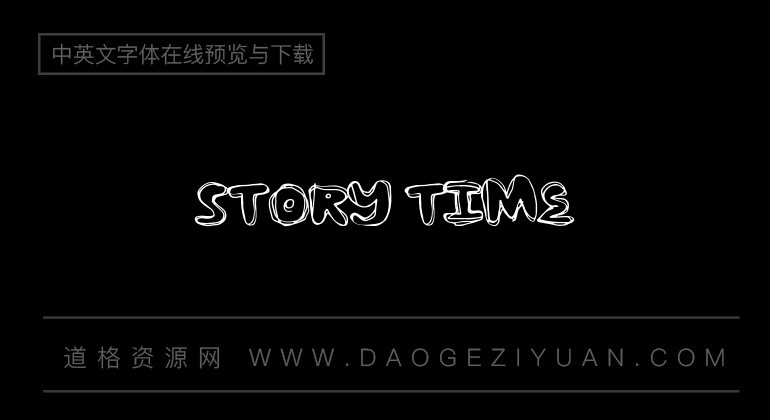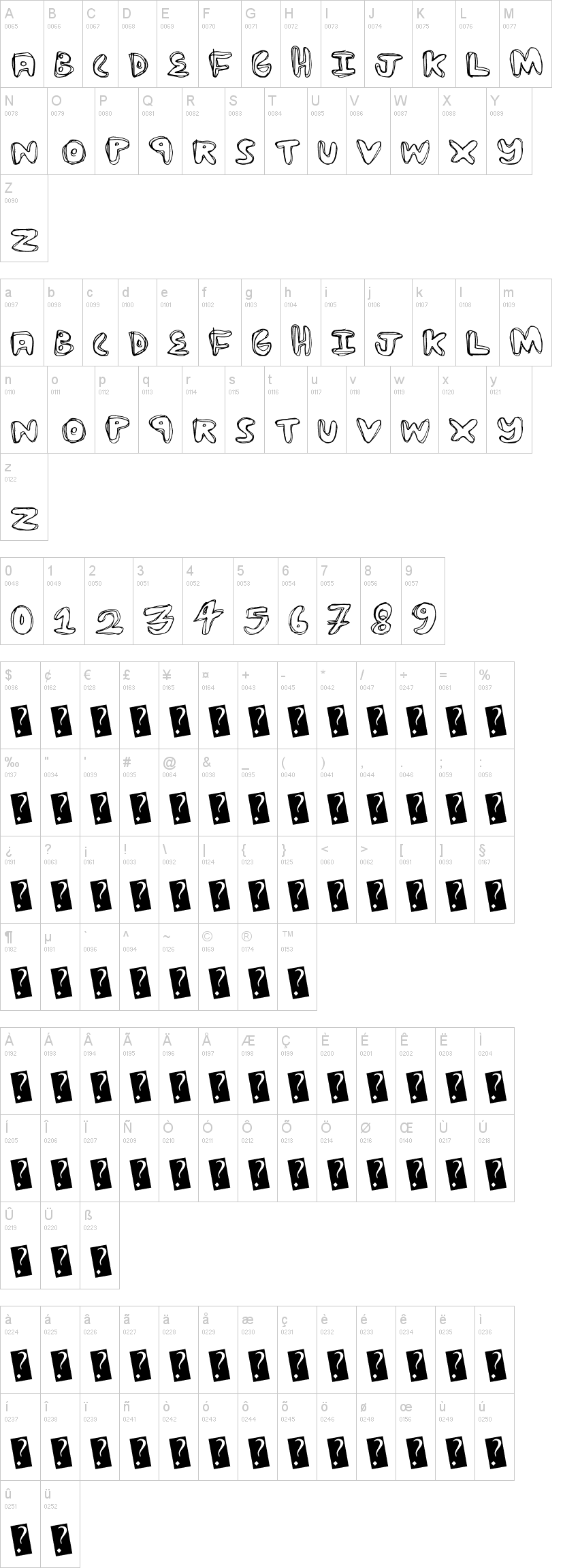
Story Time 是一款现代欧美风格字体,由 Fontfabric 公司设计,具有轻松、活泼、温暖的设计风格。它有着良好的可读性,可以用于各种类型的文本,如书籍、文章、广告等。Story Time 字体具有清晰的线条,更加精致的字形,以及更加丰富的字体组合,可以满足不同的设计需求。内容介绍
Story Time是一款非常不错的手写艺术字体,具有很好的视觉感,适合于文化类的宣传设计、商业类品牌的广告和产品包装设计以及个性化文字排版等较多场景。